Dapatkan gratis 6 font dingbat berbentuk aneka tanda panah dengan berbagai variasi.
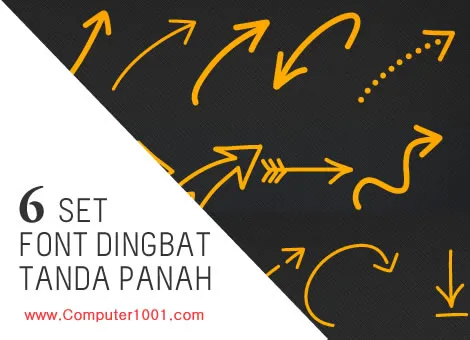
Kita bisa menggunakan tool pada aplikasi Photoshop atau fitur Shapes Microsoft Word dan PowerPoint untuk membuat bentuk tanda panah.
Akan tetapi, bagi yang belum mahir mungkin akan kesulitan membuat tanda panah yang bentuknya rumit.
Untuk itu, kita bisa memanfaatkan font dingbat yang memiliki bentuk tanda panah seperti pada kumpulan font berikut ini.
Peax Webdesign Arrows
Font dingbat ini memiliki banyak variasi pada garis tanda panahnya.
Baik yang tebal, tipis, keriting, dan titik-titik. Yang arahnya ke atas, ke bawah, ke kiri, ke kanan, dan diagonal.
PW New Arrows
Font tanda panah ini juga memiliki font dingbat bentuk diagram (chart) dan aneka teks (send, home, delete, copy, paste, dan lain-lain).
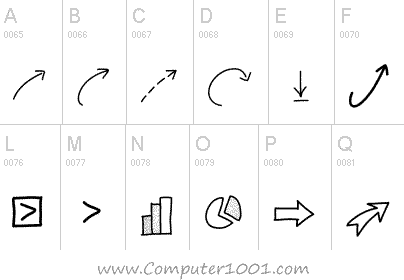
Arrows
Font ini memiliki sekitar 6 variasi tanda panah. Antara lain: bentuk lurus, melingkar, dan segitiga.
Pointers
Font ini juga memiliki aneka variasi tanda panah, seperti tanda panah segitiga dengan garisnya yang unik.
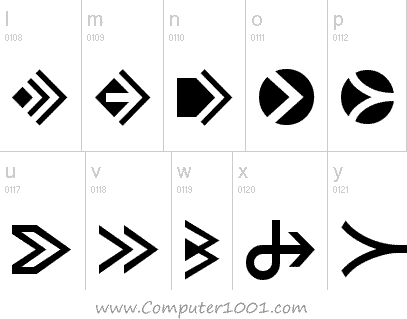
Arrow 7
Font tanda panah dengan aneka bentuk. Baik yang lurus, melingkar maupun yang bercabang seperti tanda panah penunjuk jalan.
4rrows
Font dengan bentuk tanda panah yang pendek. Sesuai untuk digunakan pada pembuatan tombol navigasi.